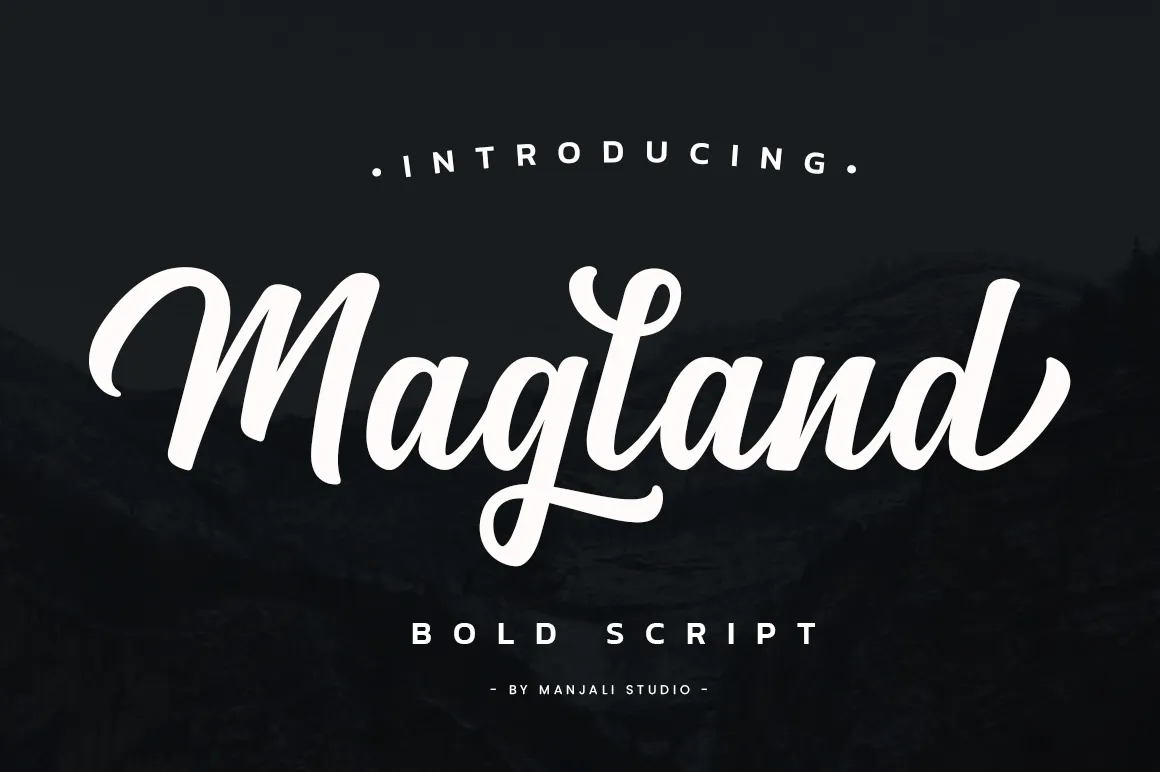
A Magland Font é uma elegante e marcante fonte feita à mão, perfeitamente projetada para dar um toque sofisticado às suas títulos e logomarcas. Com curvas suaves e linhas precisas, esta fonte define-se pela sua capacidade de fornecer um estilo notável e é ideal para qualquer projeto que esteja procurando uma paleta mais fashionista ou editorial. O PUA (Proprietary Unicode Area) de Magland significa que pode acessar facilmente todos os símbolos gerais e swashes desta fonte, permitindo-lhe explorar ainda mais as possibilidades criativas de design. Para quem está buscando um toque único e elegante em suas projetos visuais, a Magland é uma escolha perfeita.